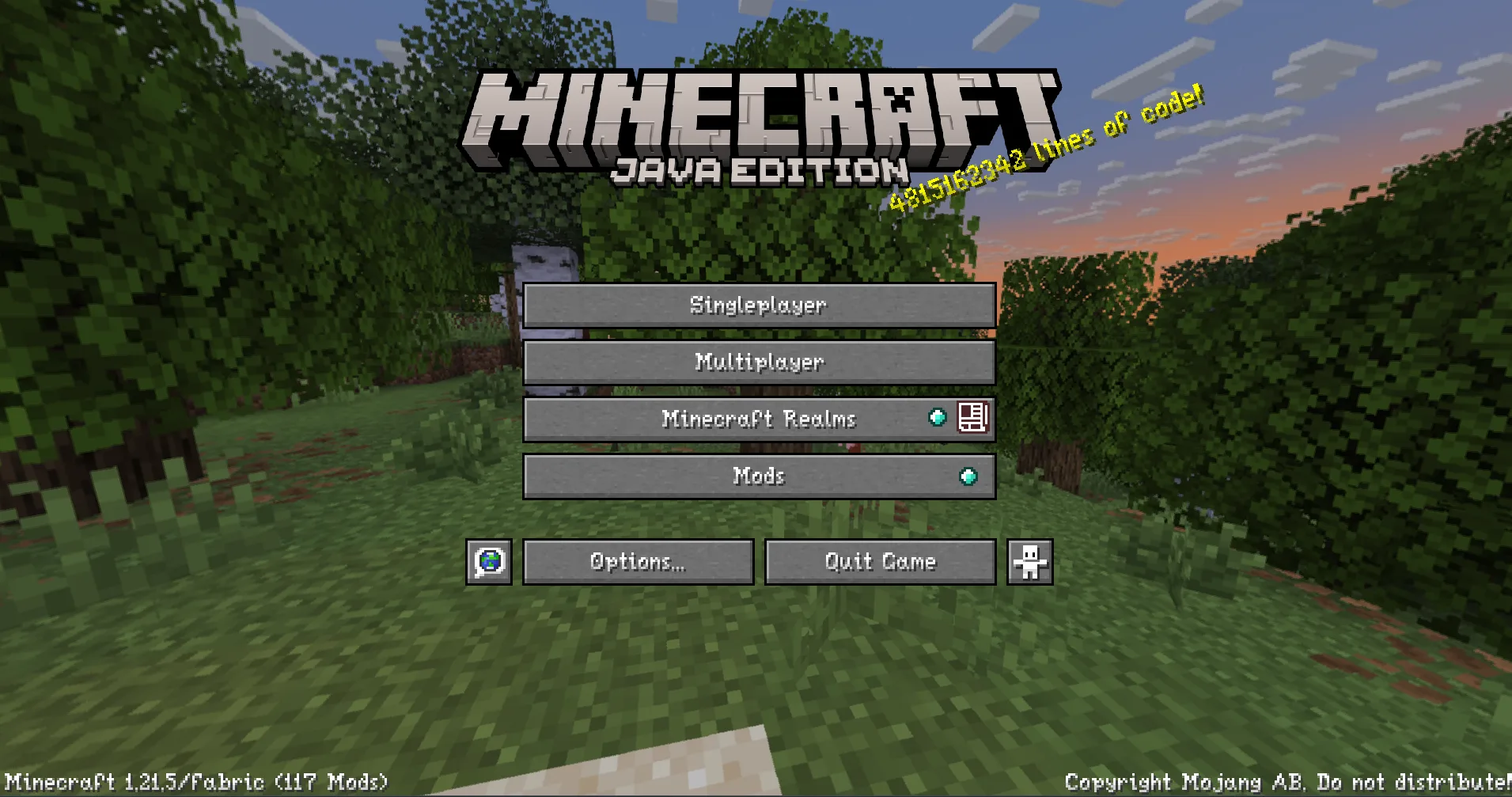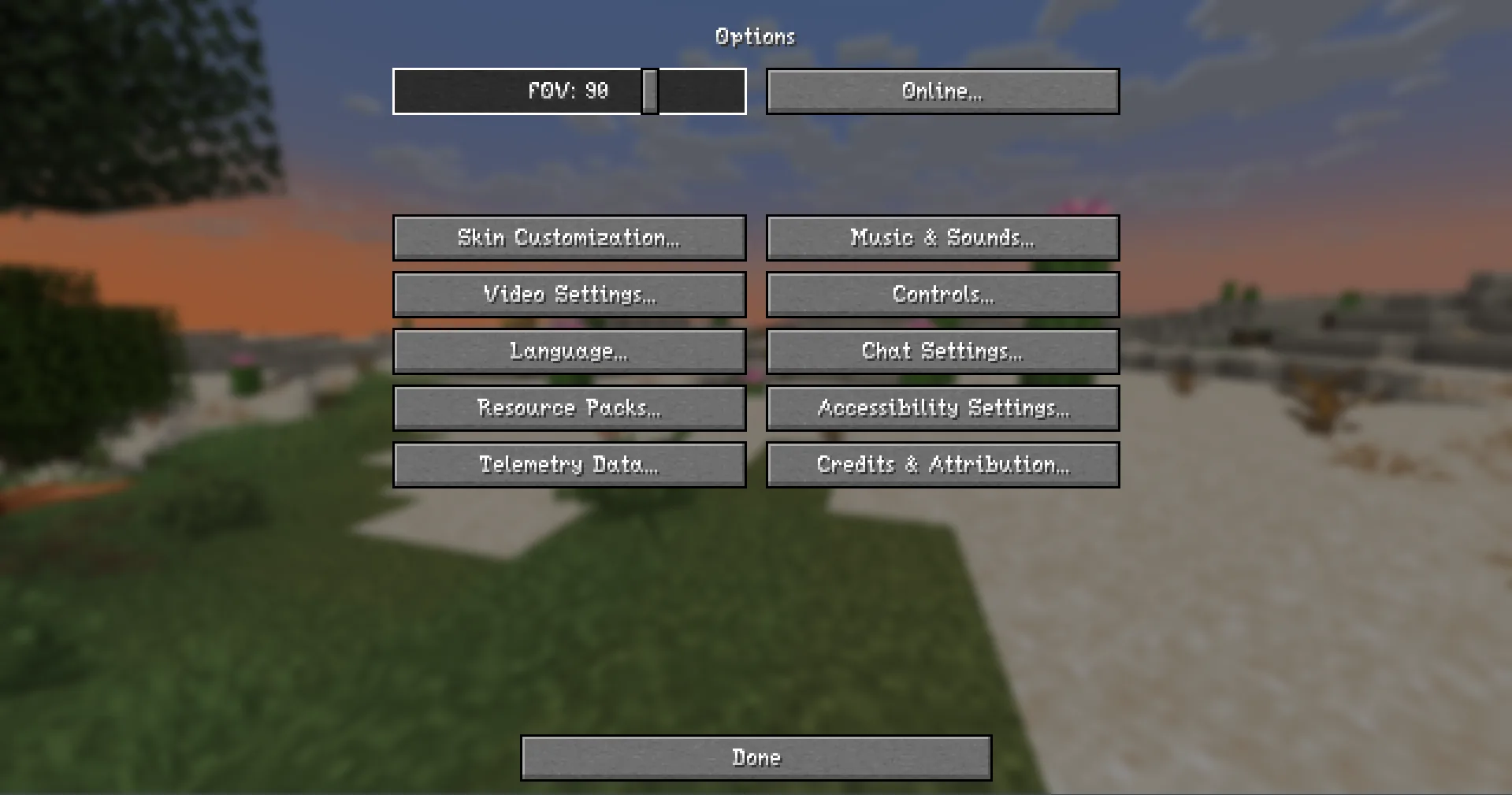
Angel's Font
Семейство шрифтовых дизайнов с уникальными характеристиками и постоянно растущим набором опций настройки. Визуально привлекательные, легко читаемые шрифты с поддержкой нескольких языков.
Angel's Font представляет собой семейство шрифтовых дизайнов с отличительными чертами и постоянно расширяющимся набором опций кастомизации. Ресурспак предлагает разнообразные шрифты, каждый со своим характером и особенностями.
Включает поддержку настройки для каждого шрифта отдельно, дизайн чернил, придающий тексту в книгах и других материалах вид рукописного письма пером и чернилами. Шрифты стильные, визуально привлекательные, легко читаемые и понятные.
Поддерживает несколько языков: английский, русский, греческий, турецкий, украинский и испанский полностью готовы. Имеет специальное издание DGS Edition, созданное для очень тёмных GUI-ресурспаков.